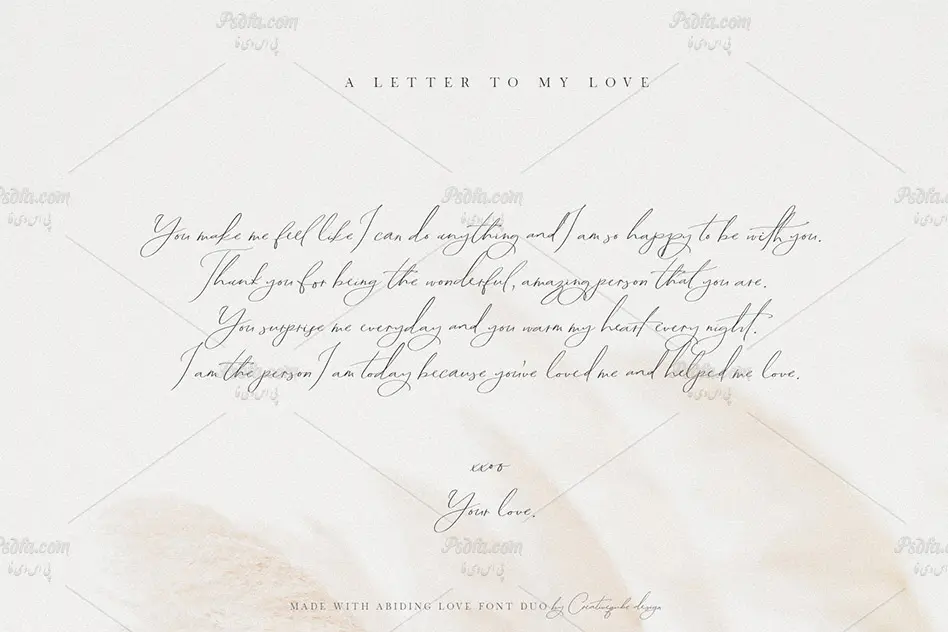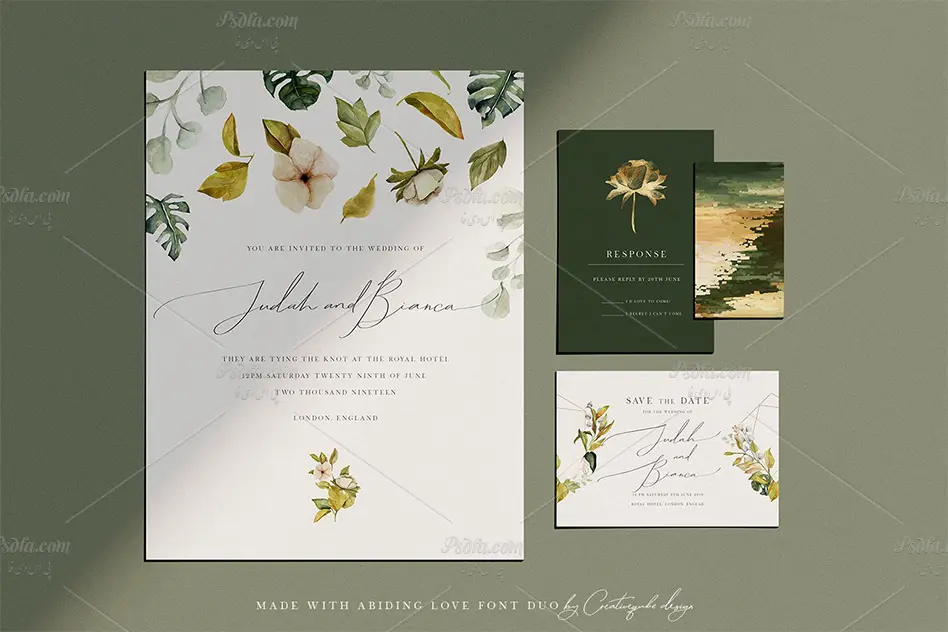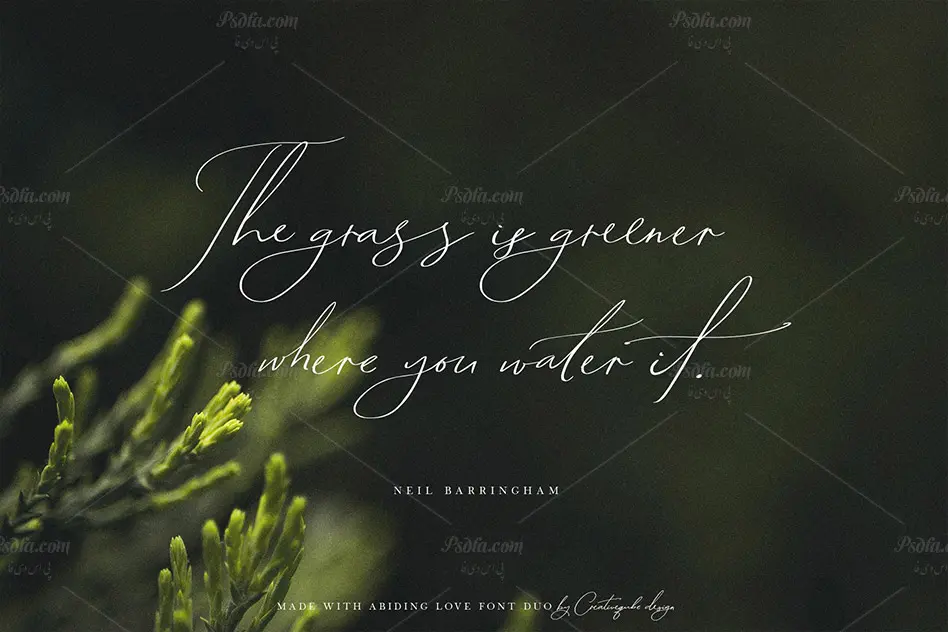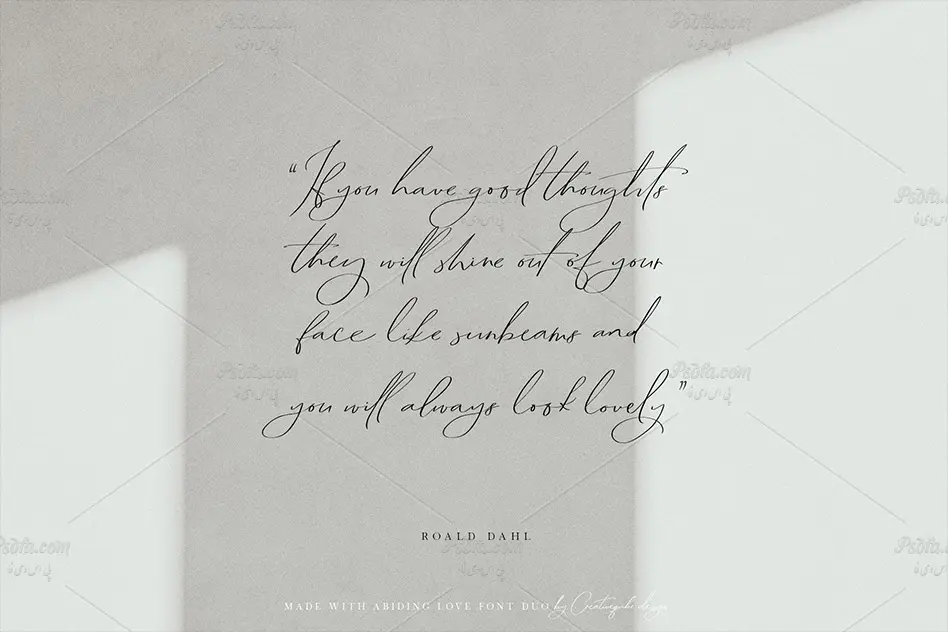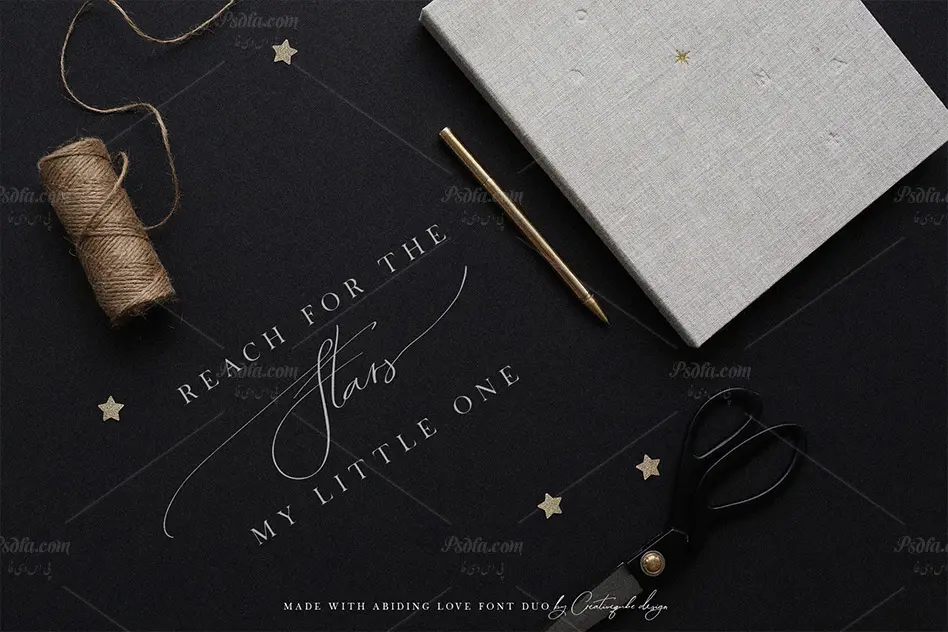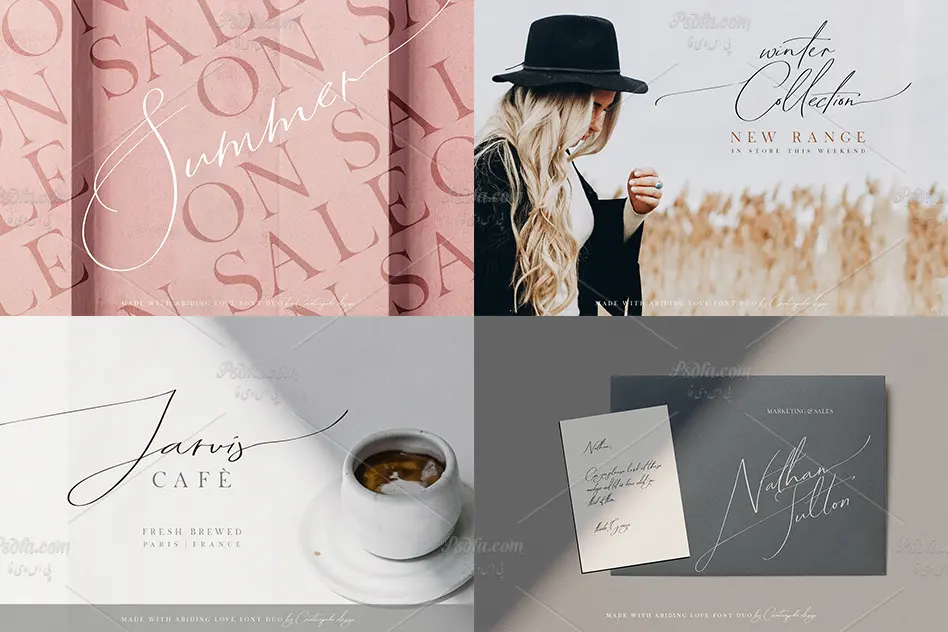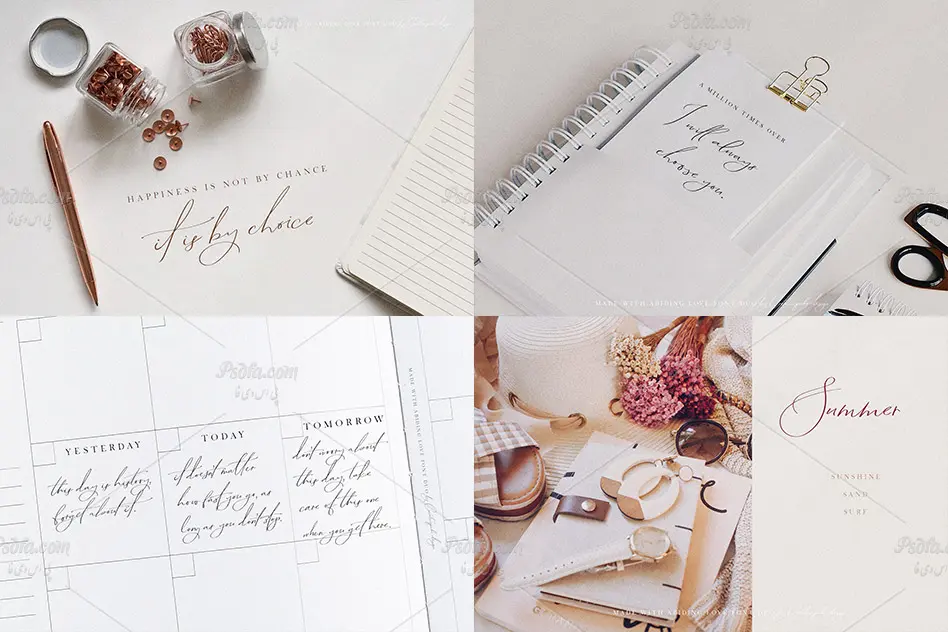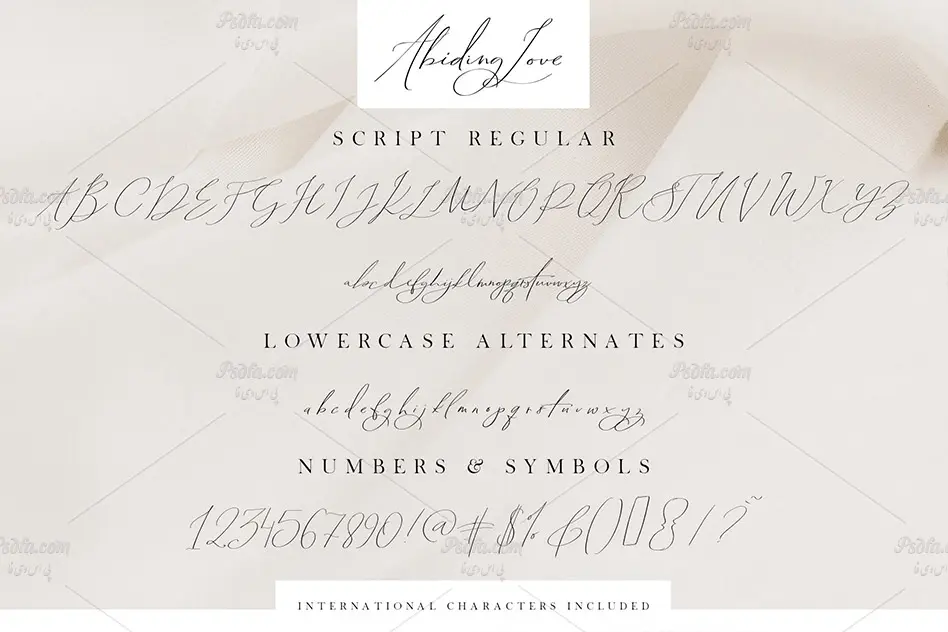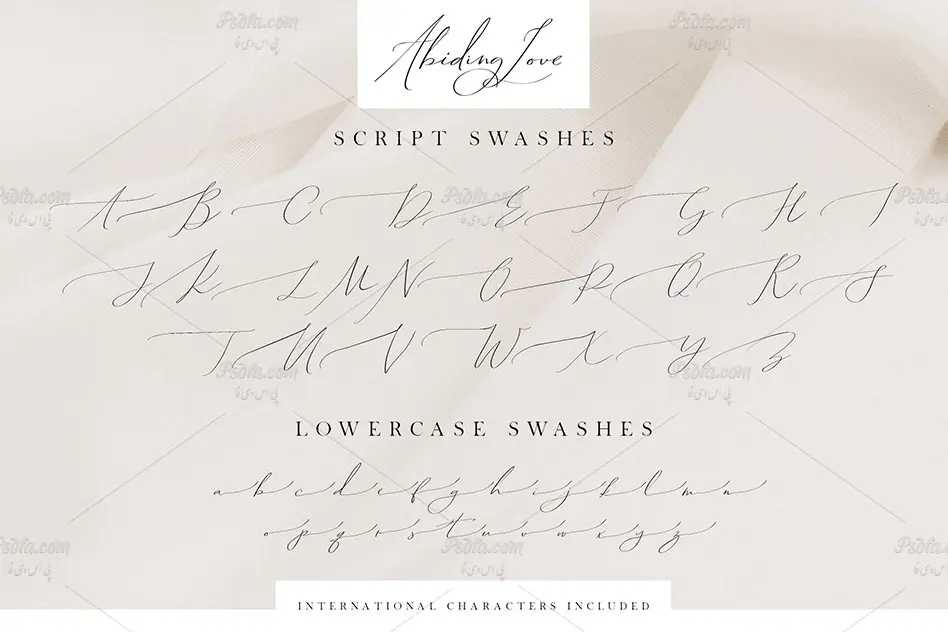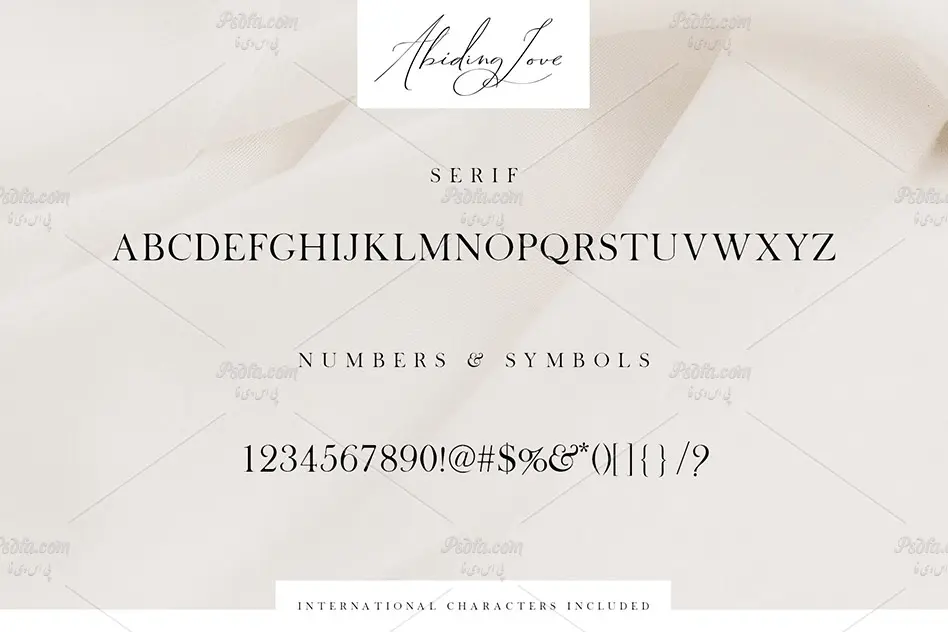
اسکریپت فونت انگلیسی عاشقانه و دستنویس Abiding Love مجموعهای از چند قلم دستنویس لاتین است که میتوان از آن در طرحهای گرافیکی به خصوص طراحی انواع کارت تبریک و کارت عروسی استفاده نمود. این مجموعه شامل 7 فونت زیبا است که در قالب فایلهای ttf, otf, woff بر روی سایت بارگذاری شدهاند. با نصب یکی از دو فرمت otf یا ttf در شاخه فونتهای سیستم قادر به استفاده از آن در تمام نرمافزارهای گرافیکی و یا ویرایشگر متن از جمله فتوشاپ، پریمیر، افترافکت، مجموعه نرمافزار آفیس و … خواهید بود. فونت Abiding Love در وزنهای معمولی (Regular)، ضخیم (Bold)، حروف بزرگ (Alt) و در طرحهای متفاوت ایجاد شده است که میتوانید از آن در طراحی انواع پوستر، کارت ویزیت، کارت تبریک، کارت پستال، بنر، بروشور، تراکت، طراحی سایت، طراحی لوگو، طراحی قالب رسانههای اجتماعی و … استفاده کنید.
- وزن : معمولی (Regular)، ضخیم (Bold)، حروف بزرگ (Alt)